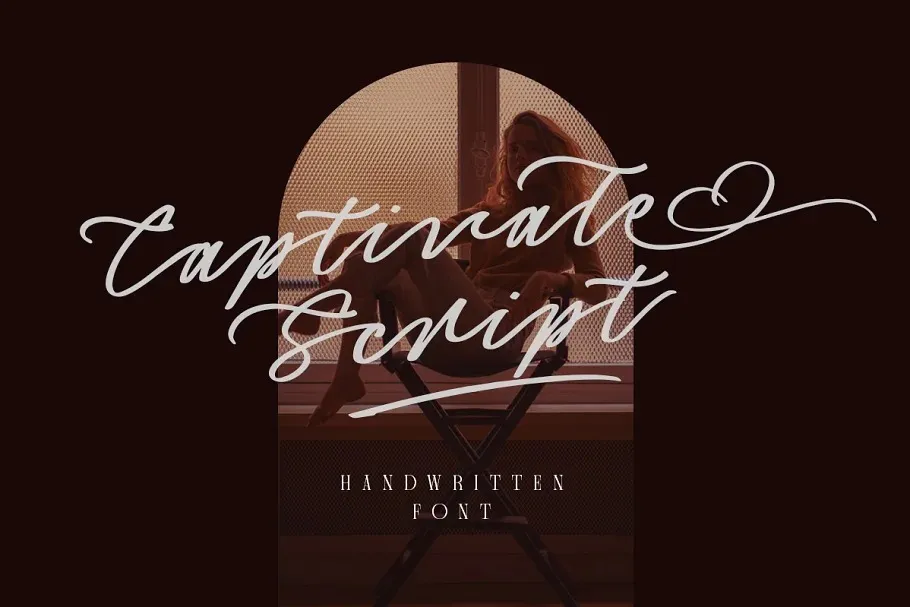
A Captivate Font é uma excelente escolha para designers que buscam uma tipografia contemporânea e moderna. Inspirada no trabalho criativo da Letterhend Studio, essa fonte apresenta formas de letras estilizadas com um toque charmoso e atual. Um destaque particular são os detalhes suaves dos swashes, que conferem ao texto um aspecto ainda mais elegante e sofisticado. Ideal para aplicações como cartões de convite casamento, embalagens, capas de livros ou até mesmo em anúncios fashion, a Captivate se destaca por sua facilidade na criação de layouts interessantes e personalizados. Seja você um profissional que deseja dar um toque especial aos seus projetos ou alguém procurando uma fonte para criar cartões de visita modernos, a Captivate definitivamente merece atenção.